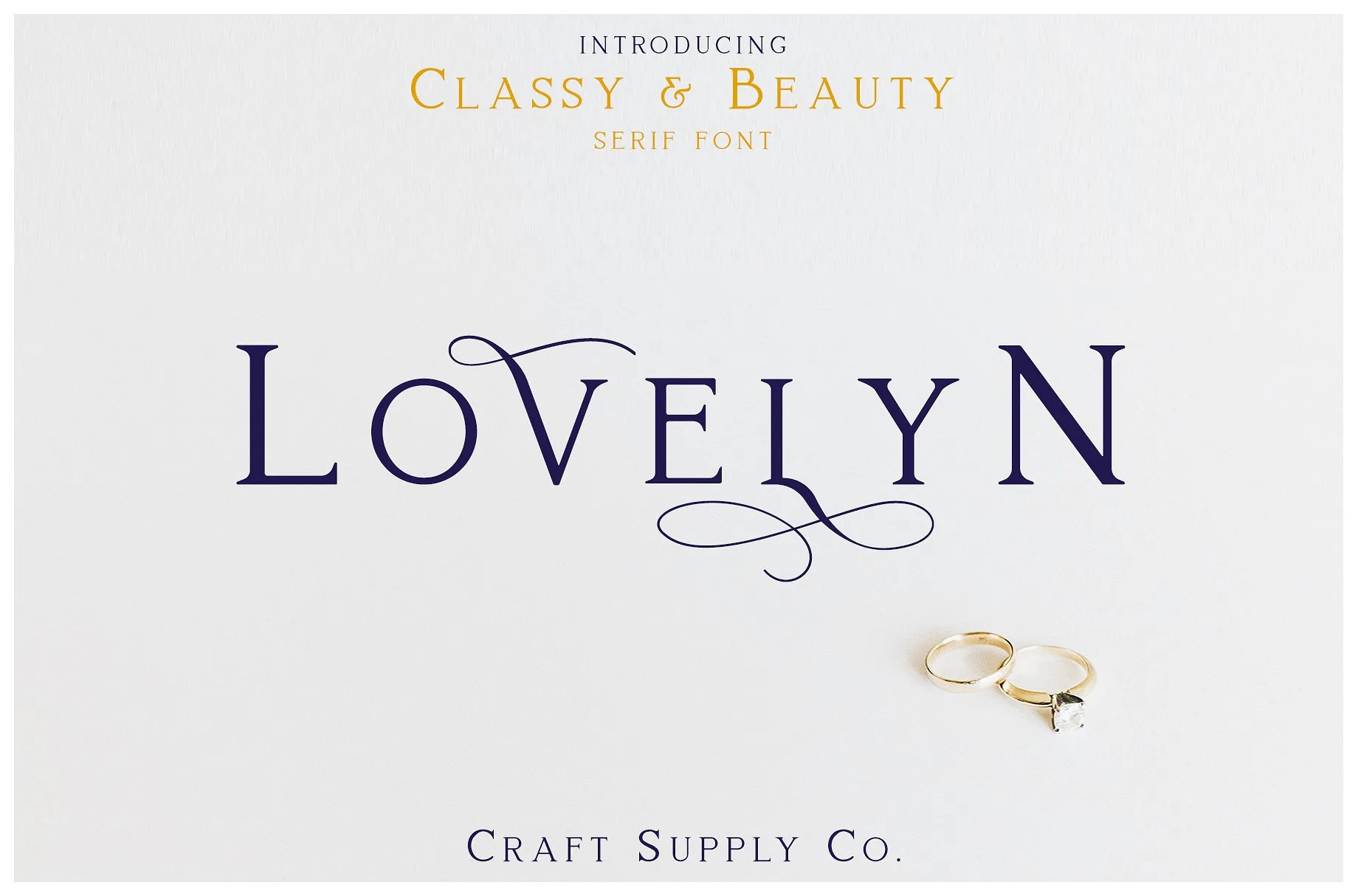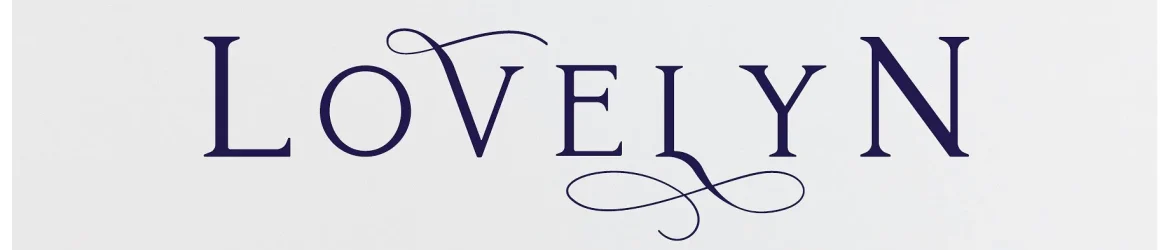
Lovelyn Font – Download Grátis
Descubra a beleza elegante e sofisticada do Lovelyn Font! Especificamente projetado para designers que valorizam uma tipografia serif elegante, este belo recurso foi criado pelo Craft Supply Co., obra-prima de Hamilton. Lovelyn é uma fonte serifa perfeita para produzir letra decorativa com um amplo leque de possibilidades. É ideal para aplicação em criações como capas de livros ou materiais publicitários, incluindo tags de embalagens e painéis. Com seu design refinado, Lovelyn oferece uma ferramenta atraente para artistas que buscam criar texturas e designs impecáveis. Se você está procurando por um recurso gráfico que dê vida à sua arte digital com elegância e profundidade, Lovelyn é definitivamente um nome a ser lembrado. Este é mais do que uma fonte; ele é uma ferramenta para transformar textos em obras de arte que ressaltam em qualquer formato de material visual.